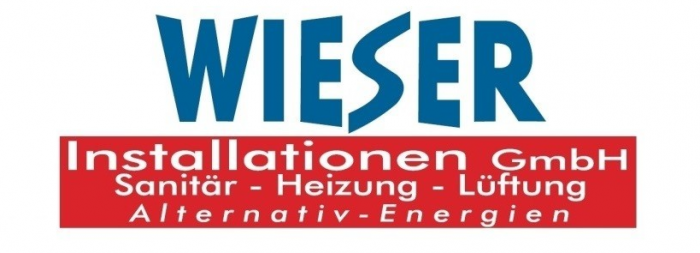
Wer kennt diese Schrift
Das wird wohl mal eine Futura oder so gewesen sein – das kannst du gleich alles so mit nachbauen und dabei, wenn es denn schon so schrecklich verzerrt sein sollen, vernünftiger zeichnen ...  :-o
… und bitte auch die restlichen verzerrten Texte wieder reparieren ;-)